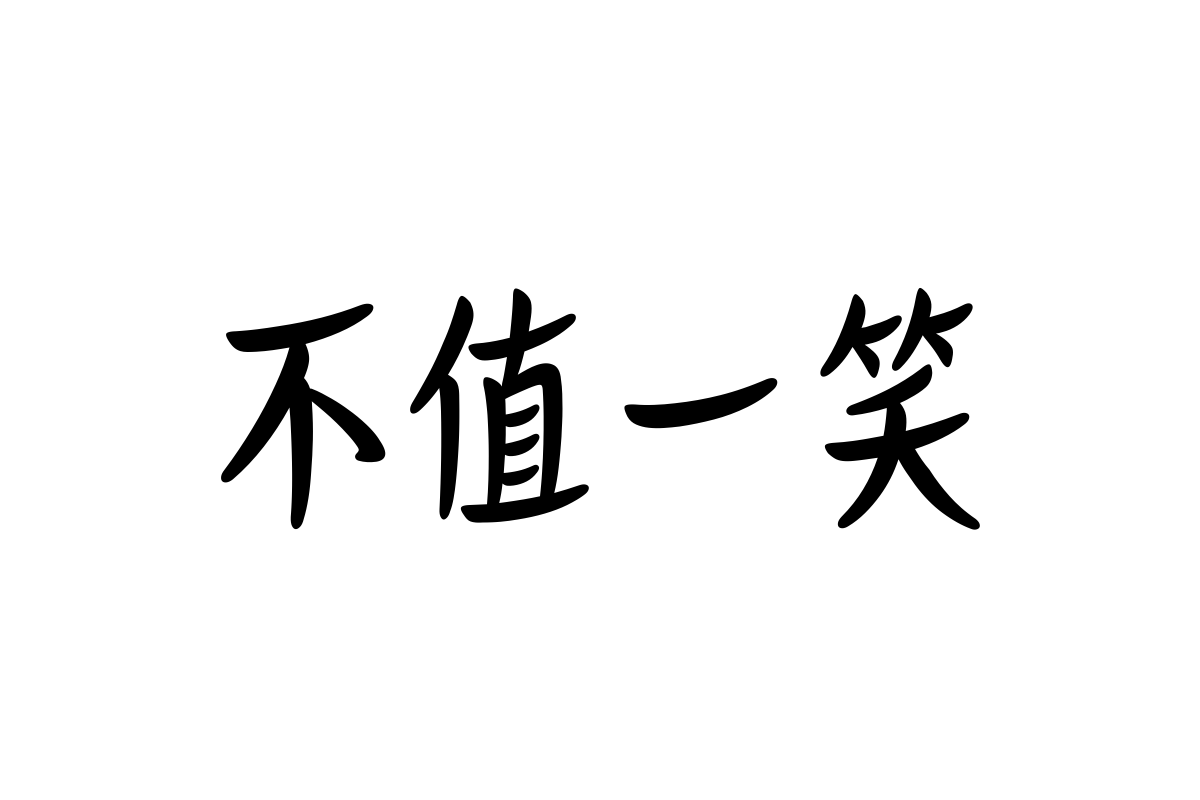
汉仪浅光65W字体是一款具有现代感的中文字体,它以其简洁、清晰的特点,深受广大设计师和用户的喜爱。这款字体的特点是笔画流畅,结构紧凑,易于阅读和书写,同时具有很强的视觉冲击力,能够吸引人们的注意力。
汉仪浅光65W字体适用于各种需要强调文字效果的场景,如广告设计、海报制作、网页设计等。它的线条粗细适中,既不会过于繁琐,也不会过于简单,能够很好地平衡整体的视觉效果。此外,汉仪浅光65W字体还具有一定的艺术性,能够为设计作品增添一份独特的魅力。
总的来说,汉仪浅光65W字体是一款非常实用的中文字体,无论是在商业还是娱乐领域,都能够发挥出其独特的优势。